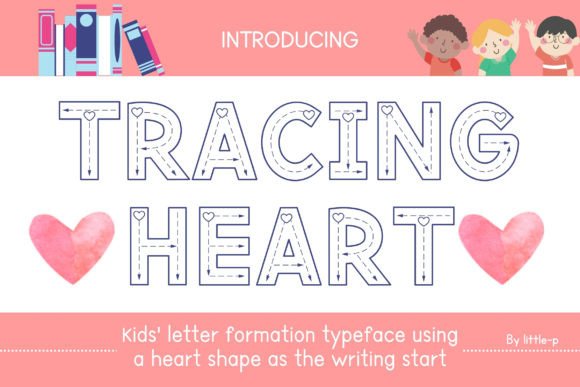
Tracing Heart
Tracing Heart – A Fonte de Traçado que Encanta e Ensina
Se você procura uma ferramenta lúdica e eficaz para melhorar o reconhecimento de letras nas crianças, Tracing Heart é a escolha ideal. Desenvolvida especialmente para o público infantil, cada caractere inicia-se com um delicado desenho de coração, tornando o processo de aprendizagem mais prazeroso e visualmente atraente.
Principais Benefícios
- Design exclusivo com corações: O detalhe do coração no início de cada letra cria uma associação positiva e desperta o interesse dos pequenos.
- Facilidade de rastreamento: Traços claros e bem espaçados ajudam a desenvolver a coordenação motora fina e a caligrafia correta.
- Versatilidade educacional: Perfeita para folhas de exercício, apostilas, cartazes, material de estudo e recursos digitais, tanto em ambientes escolares quanto em homeschooling.
- Adequada para várias idades: Ideal para alunos do jardim‑de‑infância até o ensino fundamental, acompanhando o crescimento das habilidades de escrita.
- Economia de tempo para professores e pais: Fonte pronta para uso imediato, permitindo a criação rápida de materiais didáticos personalizados.
Como Usar Tracing Heart no Dia a Dia
- Crie worksheets de caligrafia imprimindo as letras em formato grande, deixando espaço para que a criança trace o contorno.
- Incorpore a fonte em apresentações de slides ou vídeos educativos, reforçando conceitos de leitura e escrita.
- Desenvolva jogos de correspondência de letras, onde o coração serve como pista visual.
- Utilize em aplicativos de tablet ou plataformas de aprendizagem on‑line, garantindo consistência visual em todos os recursos.
Por que Escolher Tracing Heart?
Além da estética adorável, Tracing Heart foi projetada com base em princípios pedagógicos que favorecem a memorização de formas alfabéticas. Cada coração funciona como um ponto de partida intuitivo, facilitando a transição da percepção visual para a escrita manual.
Seja você professor, coordenador pedagógico ou pai dedicado, esta fonte oferece um recurso prático e encantador para estimular a escrita dos pequenos. Invista na criatividade e no aprendizado dos seus alunos com Tracing Heart – onde cada letra começa com amor.